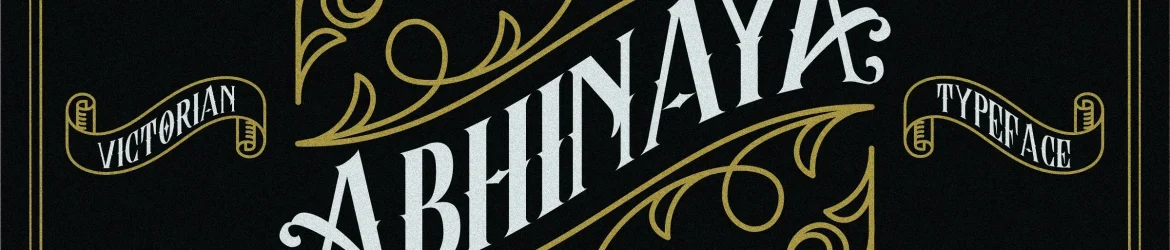
Abhinaya Typeface – Download Grátis
A Abhinaya Typeface é uma fonte serif que remete à tipografia art-deco dos anos 1920 a 1940, inspirada nos antigos estilos utilizados nas etiquetas e anúncios de embalagens. Se você aprecia a tipografia clássica e art-deco, essa fonte certamente se encaixa perfeitamente no seu arsenal de design. Introduzimos a Abhinaya Typeface, projetada pela Hamilton e compartilhada pelo Twicolabs Fontdation. Esta fonte é criada à mão, refletindo o estilo vibrante das antigos cartazes. Além dos caracteres básicos em maiúsculas e minúsculas, as variâncias sobre cada caractere incluem alternativas de aberturas opentype, ligaturas comuns, além de swashes adicionais para personalizar seus projetos. A Abhinaya Typeface é ideal tanto para logotipos quanto para o design de carta, cartazes e rótulos, sem falar dos designs de roupas ou qualquer outro tipo de aplicação visual que exigir um estilo clássico e sofisticado.